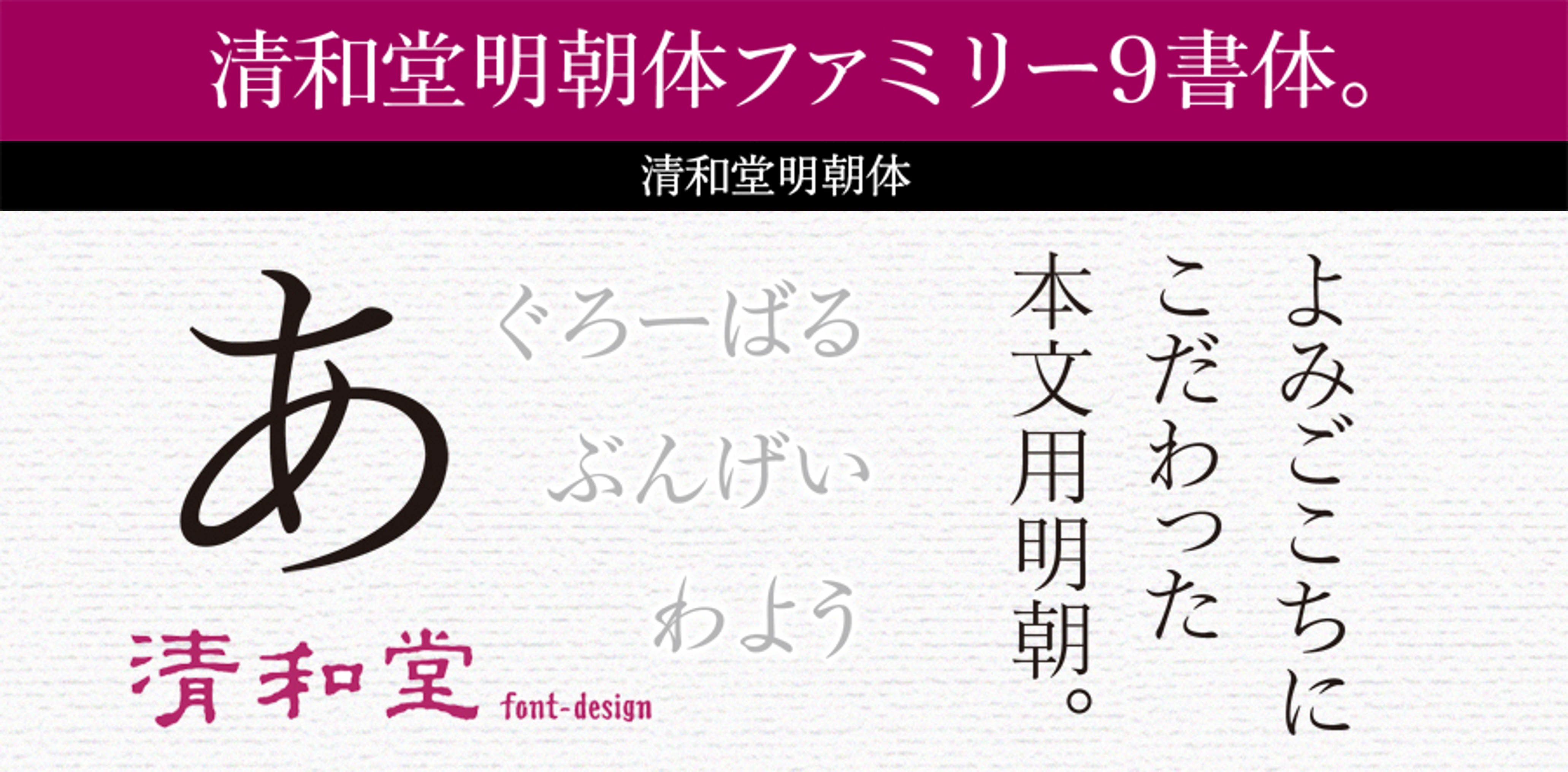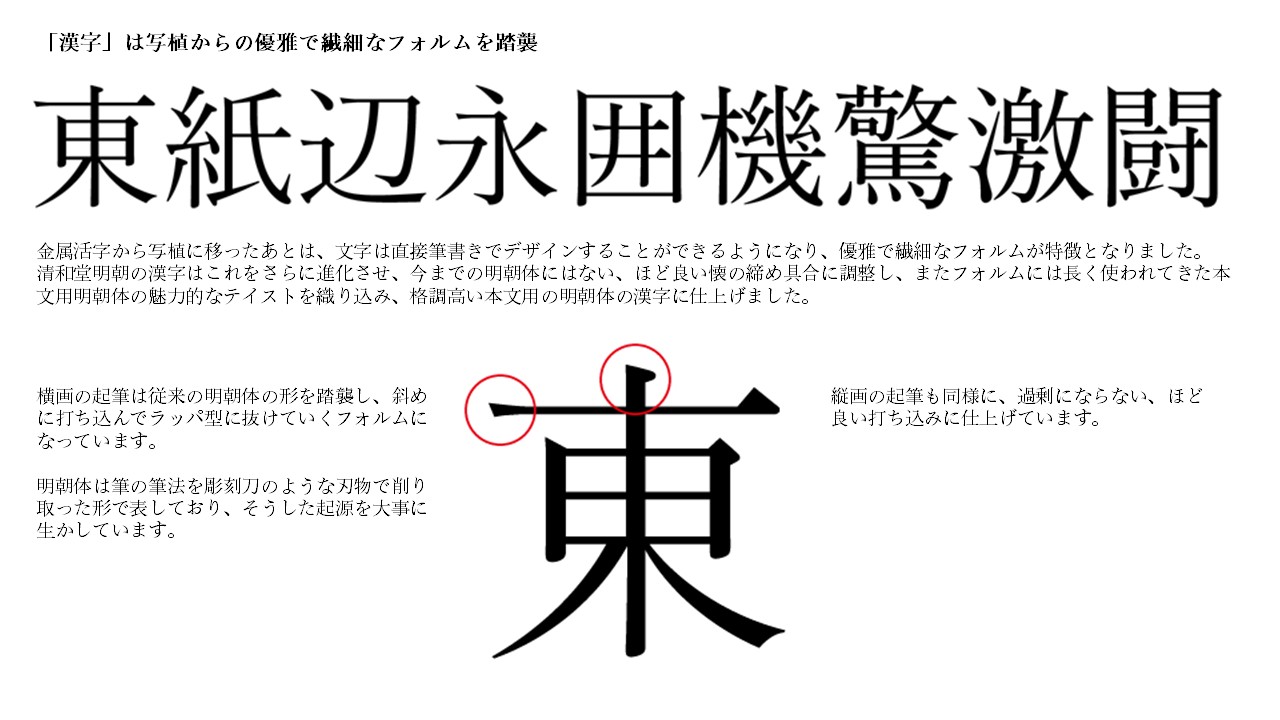
書体デザイナー 清和堂 日本のタイプファウンダリ プロフィール 清和堂は、多田信之氏が手掛けるファウンダリになります。清和堂明朝体は文字の流れをとても大切にしています。作品と読者の間に現れる特別な空気感を常にイメージして製作しました。本文用書体の奥深さを追求「読みやすさ」「心地よさ」を大切にした本文用書体をゼロから考察、清和堂明朝体シリーズを開発致しました。 さらに詳しく閉じる 代表フォント 制作フォント Can't login